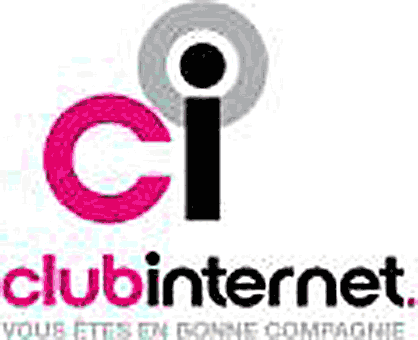
Un logo complètement déphasé:
Très embarrassé je suis d’aborder l’analyse de ce logo. Tout d’abord pour des raisons affectives, Club-Internet était mon premier fournisseur d’accès avant l’arrivée du câble, et nous a fait partager un rêve, celui d’une liberté d’expression «au coin du feu-tribal» retrouvée. Après plusieurs décennies d’un monde divisé en 4 pouvoirs (le 4e étant la presse, j’en ai «presque» oublié quels étaient les trois premiers), club-internet a ouvert en France la voix et la voie d’un cinquième pouvoir, celui des individus connectés en réseau. Et je remercie le PDG de cette société canal historique, Marie-Christine Levet, d’avoir su ré-affirmer les valeurs qui ont fondé l’arrivée des 3w en pays de France. C’est donc comme un supporter de longue date que je me suis d’abord posé la question, est-ce que le nouveau logo, la nouvelle identité visuelle du club correspond bien aux valeurs jadis et encore aujourd’hui promu par ses fondateurs.
Voici les trois logos, le premier, historique, le second et le nouveau (de gauche à droite) (mille pardons pour la qualité de reproduction mais je n’en ai pas trouvé de meilleur sur les pages de recherche).
Que remarque-t-on dans l’évolution sémantique de la marque?
Le premier visuel, un bonhomme tracé à la Picasso ou Jean Cocteau, reflète la convivialité et le One to One chers aux précurseurs du marketing. Le Club s’adresse à moi, directement par le truchement d’une illustration malhabile mais terriblement sympathique. Le petit bandeau bicolore bleu et blanc vertical, composé en caractère sans serif (gill, ou futura) concession aux modes graphiques en vigueur de cette année 1995, vient signer discrètement une image fédératrice de valeurs consensuelles (et la bascule du bleu au blanc venant mettre en valeur la syllabe [net]
La deuxième identité, plus proche de nous, doit dater (je n’ai pas pu le vérifier) de 1999 ou 2000. C’est l’époque des smileys en tous genres. Ils envahissent nos écrans, nos mails et même nos affiches 4×3 de l’époque. Elle signifie bien une tendance, une adhésion à un mouvement en marche à l’internet people comme je l’avais moi-même appelé quand j’ai créé une composition colorée pour une carte de voeux d’un de mes clients. L’intérêt évident de cette deuxième identité c’est l’intégration du logo dans un bloc-marque cohérent qui ne fait pas «pièce rapportée». Nous avons là un visuel, à forte connotation cyber-nautique qui sourit au client et le fait participer à la marche vers la modernité tout en lui décochant un clin-d’oeil complice, pas dupes, pas dupes.
Le logo s’est-il démodé trop vite? ne participe-t-il plus d’une stratégie de développement englobant l’ensemble des services (phone-télé-internet-jeux-etc.) que doivent proposer les FAI pour rester dans la compétition, un autre interview de Marie-Christine Levée nous éclaire davantage sur le modèle économique en marche de ces opérateurs. Les questions que je me pose, les services marketing, de communication se les sont posés également.
Démodé trop vite…? Est-ce que Coca Cola s’est démodé trop vite, ou la Vache qui Rit, ou encore le logo de monsieur Boursin. Combien de fois Renault a-t-elle (la firme) changé de marque au cours de son histoire? Pas tant que ça. 3 fois, 4 fois, allez 5 fois tout au plus… Est-ce le devenir d’un logo de se démoder? oui sans doute, mais sa fonction, et là on est au plus profond de la question n’est pas d’être «à la mode», mais de représenter une entreprise, des produits, des services et des acteurs sociaux… salariés, clients, un environnemental de partenaires. Un logo doit pouvoir supporter le vieillissement que dis-je, la maturation d’une industrie. Or le fait significatif ici, c’est que les services liés à Internet relèvent d’une véritable révolution planétaire. Dans les esprits, dans les comportements transactionnels (achats, piratages, consultations, recherche de documents etc.). Une étudiante argentine m’a remerciée aujourd’hui pour l’avoir aidée au travers de mon blog à résoudre un problème graphique que lui a posé son prof… à Buenos Aires
Alors je comprends bien la fébrilité des entrepreneurs, des dirigeants des FAI de coller aux événements, à l’histoire de leur évolution. Ça va vite, et encore plus vite qu’on croit. Mais alors il est une question qu’on est en droit de se poser. Pourquoi et comment est-on arrivé à la solution du nouveau logo? En quoi ce logo participe-t-il à la modernité du paysage inter-nautique, cybermachin et nano-high-techno-folie?
Analyse de la forme :
partie supérieure : deux lettres [c] et [i] composés pour le [c] en avant garde bas-de-casse (minuscule), et le [i] en gill parce que surmonté d’un point rond caractéristique. Mais je peux imaginer un mix entre des lettres en Avant Garde de Lubalin et un point rond rapporté du Gill.
Le cercle gris entourant le point du [i] est presque aussi grand que l’oeil de la lettre [c]. Ce qui fait que lorsque vous clignez l’oeil, au lieu de voir ci, vous lisez cio, ou bien coi. Permettez-moi de balayer d’avance les objections du style : «vous exagérez, vous découpez les cheveux en 1000 etc.» La typographie et le graphisme des logos s’adresse autant à nos yeux qu’à nos inconscients. Combien de gens savent qu’ils ont deux nerfs vestibulaires n°8 qui participent à la transmission des informations concernant l’équilibre de notre corps. Qu’en l’absence de ces nerfs le cerveau ne sait plus interpréter le haut et le bas, la gauche de la droite. Ça vous empêche pas de vivre de pas savoir. Le graphisme d’un logo est porteur de signes, de signifiants dont l’organisation, le rythme, les couleurs participent à l’imprégnation dans notre cerveau d’éléments signifiés. Et cela ne passe pas forcément par la conscience. La plupart du temps cela se fait à notre insu et les agences de design connaissent ces règles depuis le début de notre histoire moderne. Les lettres alphabétiques représentent des sons. Le [Cé], le [i], et puis il y a un [o] qui traîne là, au milieu de nulle part que notre conscience n’ose même pas prononcer tant il est resté en arrière, en gris d’ailleurs voulu par le graphiste. Mais ce [o] vient brouiller les sons initialement perçus. Et c’est un fait. Cela ne s’invente pas.
Et puis sous ce [c] rose fuchsia, et ce [i] noir surmonté d’un [o] gris qui devrait normalement nous faire penser à une cible (on se demande d’ailleurs s’il s’agit de nous en tant que clients, ou bien du marché de l’internet en général, l’intention étant trop floue), il y a La Signature [club-internet].
Composé en caractère Blippo ou équivalent, ce caractère date du début des années 70. Il représente un double ana-chronisme:
Tout d’abord et naturellement si je dois typographier un logo d’aujourd’hui pour aller vers demain, je ne vais pas utiliser une police de caractère qui date de 1970. C’est trop restrictif, par rapport à une politique marketing qui vise toutes les audiences, tous les CSP…